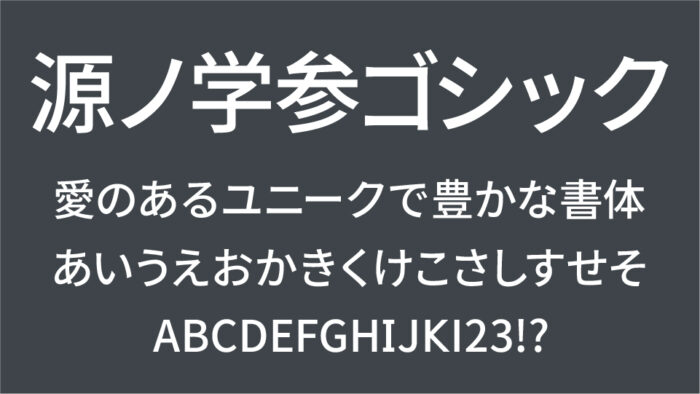
源ノ学参ゴシック
源ノ学参ゴシックフォントは、「源ノ角ゴシック TC」、「源ノ角ゴシック SC」、「源ノ角ゴシック JP」をベースにして作られてたゴシック体フォントです。
学参フォントは 「正しく・読みやすく・教育的配慮がされた文字」 として文部科学省の学習指導要領に準拠した字形を持つフォントのことです。
主に小学生から高校生向けの教科書やドリル、学習プリントなどで使われることが多い文字で、教科書体に近いデザインで、正しい字形を学べるように工夫されています。
「とめ・はね・はらい」が明確に表現されており書写の練習にも活用できるフォントです。